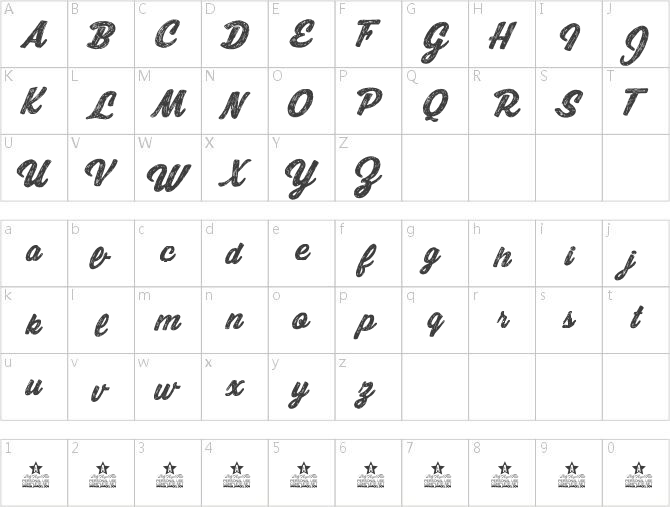
Moon Walker Personal Use
Moon Walker Personal Use介紹
Moon Walker Personal Use字體字庫是一款讓人賞心悅目、百看不厭的英文字體,適合各類廣告和產品包裝設計應用,字體大小0.31MB,格式為ttf字體,上傳用戶是伍佰,作者/版權方為未知
Moon Walker Personal Use效果圖